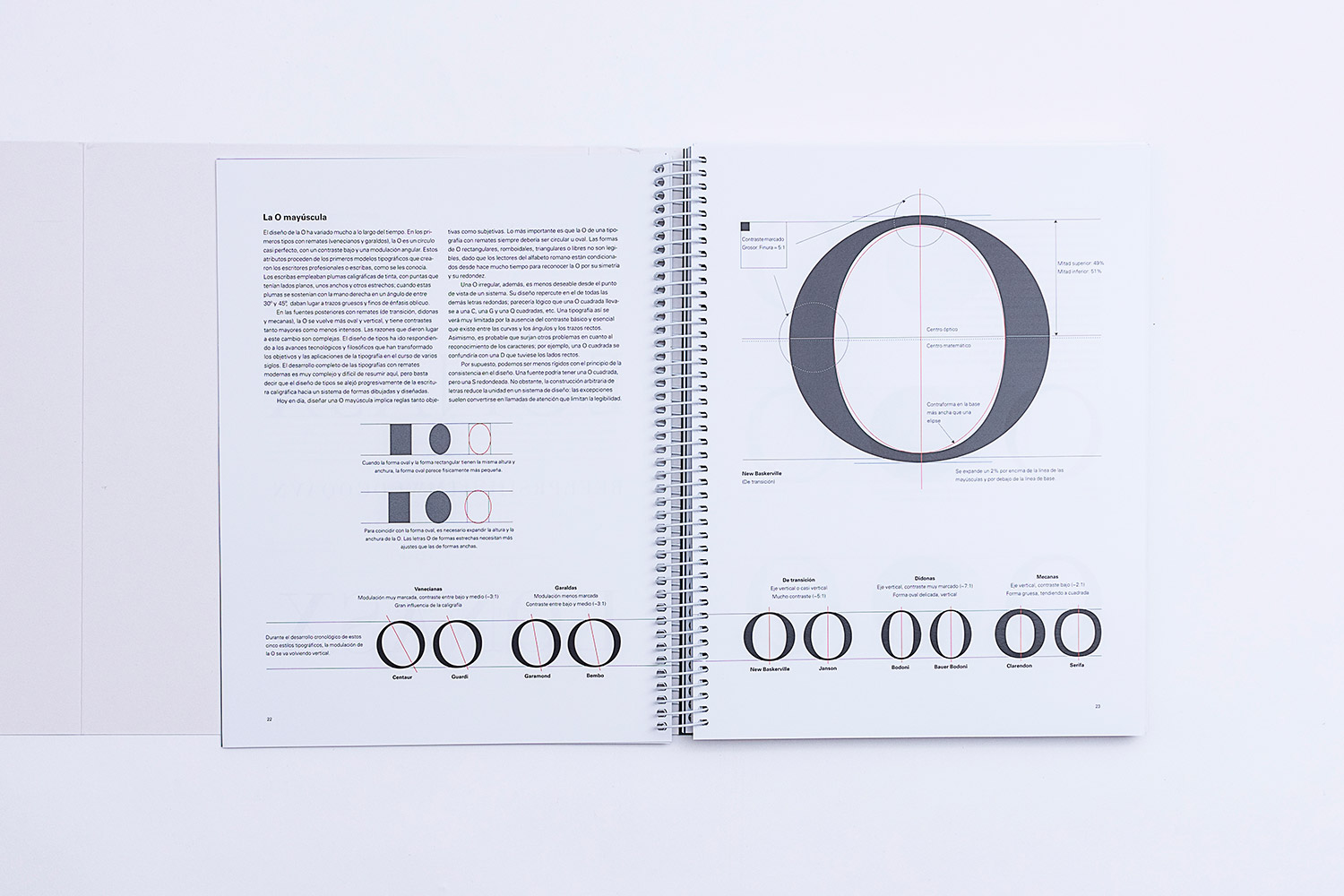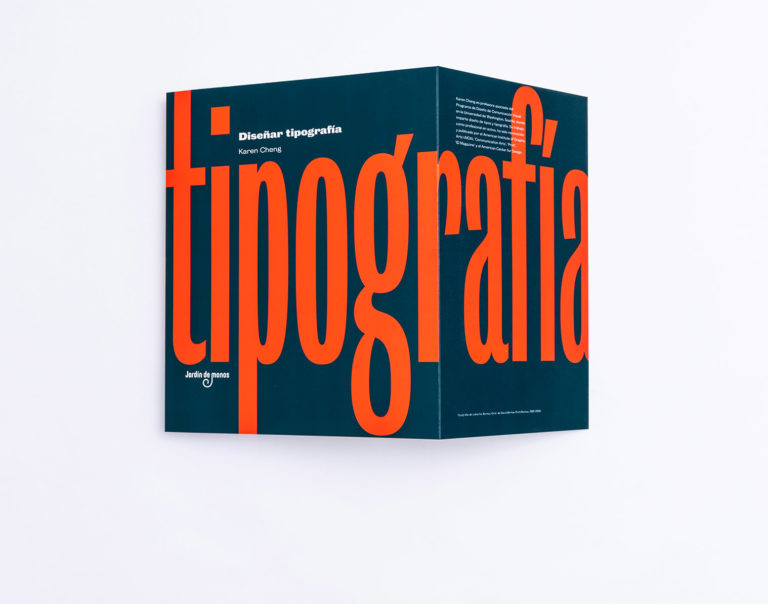
Diseñar tipografía, de Karen Cheng
Dando saltitos de alegría estamos desde que nos enteramos que una de nuestras editoriales favoritas (y amigas), Jardín de Monos, acaba de lanzar una nueva referencia al firmamento de obras imprescindibles. Todos los miembros de Rayitas azules somos muy lectores, y cuando nos tocan la fibra profesional con un nuevo libro, sea sobre tipografía, o consagrado al diseño editorial, no podemos sino hacernos eco del mismo, y, como siempre, aportar una buena ración de fotos, para mostrarlo en todo su esplendor y gloria.Curiosamente, tanto el título de este nuevo libro, como el anterior, contienen «diseñar» o «diseño», aludiendo involuntariamente a los principios que Jardín de Monos sostienen como editorial: pragmatismo y espíritu docente.
Un clásico, reeditado de nuevo en español
Al igual que ocurrió con su primera referencia, Diseño para la edición, los monos editores recogen el testigo dejado por otras editoriales. En el caso de Diseñar tipografía, Gustavo Gili ya lo editó a principios de los «dosmiles». No obstante, hay que recalcar que no sólo se han limitado a reproducir su contenido, sino también a mejorar ostensiblemente su empaque, como veremos algo más abajo.
‘Diseñar tipografía’ nos ayudará a generar mejores bocetos de nuestros proyectos tipográficos.
En la actualidad, Karen Cheng es profesora de Diseño Visual y Comunicación en la Escuela de arte, Historia del Arte y Diseño de Washington. Fue en 2006 cuando Designing Type (nombre original de la obra) vio la luz de la mano de, nada menos, la Yale University Press. Desde entonces, Diseñar Tipografía se ha traducido al alemán, coreano, francés y chino. Asimismo, no falta en ningún ranking de mejores libros de tipografía con criterio, como el nuestro.
Acabados meditados: encuadernación canadiense
El look & feel del libro es buenísimo.
Si algo llama la atención al sostener la obra por primera vez, es su generoso formato y encuadernación canadiense. En palabras de la propia Jardín de Monos:
«Lo malo de todas las demás ediciones del Cheng es que era una pesadilla trabajar con ellos como libro de consulta. El papel, de muy buena calidad y alto gramaje, con una encuadernación cosida en rústica, hacía que su uso cotidiano fuese una batalla permanente, y obligaba a tener que utilizar pesas y pesos para mantenerlo abierto en la mesa, o en el atril de trabajo.
De ahí que de cara a esta edición optáramos por una encuadernación a la canadiense. El Wire-O envuelto por cartulina gráfica, aporta 2 cosas a esta edición:
Por un lado, tiene la elegancia de un libro tradicional, con su lomo y todo. Por otro lado es muy manejable, fácil de usar como manual de consulta, lo que muchos profesores y alumnos, así como profesionales, agradecerán. Es el Cheng que me hubiera gustado tener cuando lo tenía que usar».
Sólo tenemos que apreciar las fotos para darnos cuenta de lo fácil que resultará acoplar y manejar la publicación, mientras tenemos Glyphs, o nuestra libreta de bocetos tipográficos, abiertos.
La encuadernación en wire-O, redunda en un uso mucho más operativo de la obra como manual de trabajo.
¡Ojo! El carácter pragmático de la encuadernación, no impide que Ángel Olmos, cofundador de la editorial, no haya aprovechado para «jugar» con el mismo. De esta forma, el título se extiende a lo largo de cubiertas, lomo, y solapas, creando un golpe de efecto de los que tanto nos gustan, y generando valor. ¡Bravo!
¿Sólo para profesionales?
A diferencia de la primera referencia de Jardín de Monos como editorial, Diseño para la edición, Diseñar tipografía tiene un target indudablemente más especializado. No obstante, esto no impide que resulte tremendamente útil para un público diseñador más general (aunque no se dedique a diseñar tipografía en sí).
Toda la sección introductoria de la obra, está dedicada a la clarificación de terminología asociada y principios básicos: variables tipográficas, anatomía, clasificación… Todo profusamente ilustrado.
La parte inicial de la obra, clarifica aspectos esenciales inherentes, no sólo al diseño de tipografías, sino a la gestión de las mismas por parte de los diseñadores.
Las ilustraciones con superposiciones, ayudan muchísimo a entender mejor la compleja naturaleza anatómica de los diferentes caracteres.
Por otro lado, las distintas secciones dedicadas a los diferentes grupos de glifos (mayúsculas, minúsculas, signos diacríticos, espaciados, etc.), nos ayudan a entender qué aspectos debemos cuidar para que un carácter esté bien diseñado, y, por tanto, nos aportan criterio como diseñadores de cara a elegir una tipografía legible, por ejemplo para cuerpo de texto.
«La tipografía siempre ha sido casi como el cuento de Poe, ‘La carta’, tan expuesta, tan pública y a la vez tan invisible.»
Por otro lado, el diseñador de tipos, destinatario principal de Diseñar tipografía, no echará de menos ningún detalle o aspecto, tal y como nos apuntan desde Jardín de Monos:
«Empezamos a usar el Cheng en edición americana, o quizás inglesa, hasta que GG sacó la suya allá por 2006. Cheng aportaba un estudio muy detallado de las relaciones tan poco evidentes entre las diferentes partes de las letras, con otros caracteres. Su agrupación era lógica y muy bien estructurada, minúsculas, mayúsculas, con serifa, y sin ella, signos diacríticos y numerales.